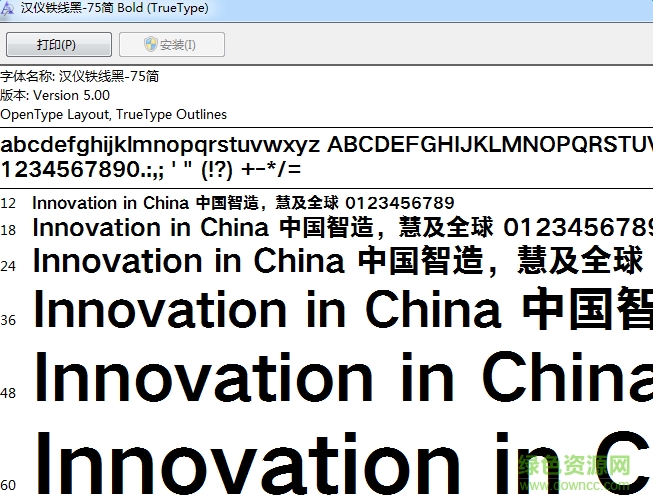
漢儀鐵線黑 75簡(jiǎn)
漢儀鐵線黑 75簡(jiǎn) bold字體是漢儀鐵線黑系列字體中的一款,該字體非常有個(gè)性,可以廣泛應(yīng)用于廣告設(shè)計(jì)、宣傳海報(bào)、ppt、影視制作以及任何使用文字的領(lǐng)域,有需要的朋友可以免費(fèi)下載收藏。
漢儀鐵線黑75簡(jiǎn)bold字體
漢儀鐵線黑 75簡(jiǎn) bold字體是一款漢儀字體庫中的個(gè)性字體,字型非常大氣,有喜歡的朋友就來綠色資源網(wǎng)下載使用吧!